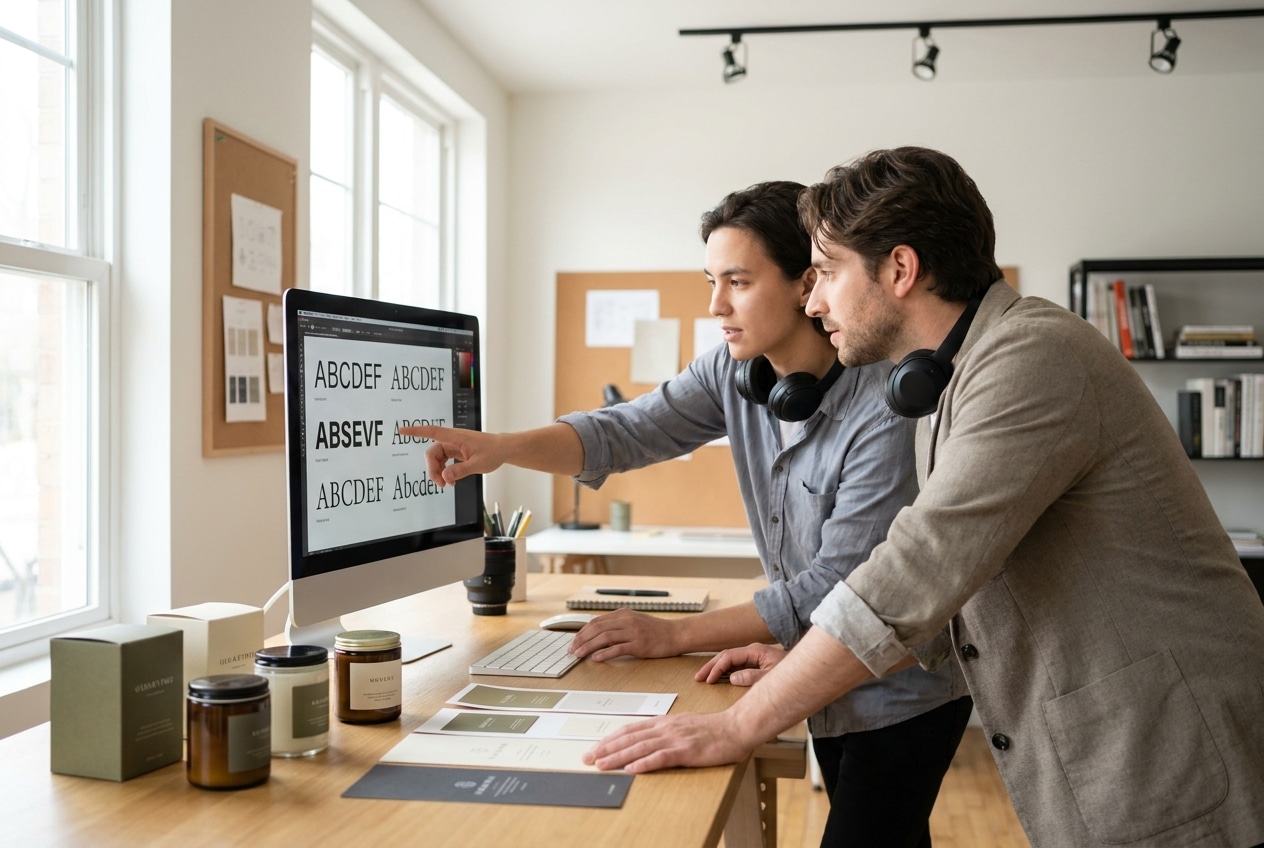
เทคนิคเลือกฟอนต์ออกแบบป้ายและฉลากสินค้า ให้แบรนด์ดูโปร
ฟอนต์หรือรูปแบบตัวอักษรไม่ใช่เป็นเพียงองค์ประกอบเพื่อความสวยงาม แต่คือ “เสียง” ของแบรนด์ที่สื่อสารกับลูกค้าโดยตรง การเลือกฟอนต์ที่เหมาะสมสามารถยกระดับสินค้าธรรมดาให้ดูพรีเมียม สร้างความน่าเชื่อถือ และทำให้แบรนด์เป็นที่จดจำได้ในทันที ในทางกลับกัน การเลือกฟอนต์ที่ผิดพลาดอาจทำให้สินค้าดูด้อยค่าและไม่น่าสนใจ
หัวใจสำคัญของการเลือกฟอนต์ที่มืออาชีพใช้
ก่อนจะลงลึกในรายละเอียด มีหลักการสำคัญที่ควรทำความเข้าใจ เพื่อเป็นแนวทางในการตัดสินใจเลือกฟอนต์สำหรับงานออกแบบโลโก้ ป้ายโฆษณา และฉลากสินค้าให้มีประสิทธิภาพสูงสุด
- ความอ่านง่าย (Readability) คือหัวใจสำคัญที่สุดของการออกแบบป้ายและฉลากสินค้า ข้อมูลต้องถูกสื่อสารอย่างรวดเร็วและชัดเจนบนชั้นวางสินค้า
- ความสอดคล้องกับแบรนด์ (Brand Consistency) ฟอนต์ต้องสะท้อนบุคลิกของแบรนด์ ไม่ว่าจะเป็นความหรูหรา, ความทันสมัย, ความเป็นธรรมชาติ หรือความสนุกสนาน
- ความเรียบง่าย (Simplicity) การใช้ฟอนต์จำนวนน้อย (ไม่เกิน 2-3 แบบ) และสร้างลำดับชั้นของข้อมูลที่ชัดเจน คือกุญแจสู่การออกแบบที่ดูเป็นมืออาชีพและไม่รกสายตา
การเรียนรู้ เทคนิคเลือกฟอนต์ออกแบบป้ายและฉลากสินค้า ให้แบรนด์ดูโปร เป็นทักษะที่จำเป็นสำหรับผู้ประกอบการ SME และนักออกแบบที่ไม่ควรมองข้าม เพราะฟอนต์มีอิทธิพลโดยตรงต่อการรับรู้ของผู้บริโภค มันสามารถสร้างความประทับใจแรกพบ บอกเล่าเรื่องราวของแบรนด์ และสื่อสารข้อมูลสำคัญของผลิตภัณฑ์ได้อย่างมีประสิทธิภาพ การเลือกฟอนต์ที่ถูกต้องไม่เพียงแต่ช่วยให้ฉลากสินค้าดูสวยงาม แต่ยังเป็นเครื่องมือทางการตลาดที่ทรงพลังในการสร้างแบรนด์ให้โดดเด่นและน่าจดจำในตลาดที่มีการแข่งขันสูง
ในโลกธุรกิจปัจจุบันที่ลูกค้าตัดสินใจซื้อสินค้าในเวลาเพียงไม่กี่วินาที ป้ายและฉลากสินค้าจึงเปรียบเสมือนพนักงานขายที่เงียบที่สุด การออกแบบองค์ประกอบทุกส่วนอย่างพิถีพิถัน โดยเฉพาะการเลือกใช้ตัวอักษร จะช่วยดึงดูดสายตา สื่อสารคุณค่า และสร้างความไว้วางใจได้ทันที ความรู้นี้จึงเป็นสิ่งจำเป็นสำหรับเจ้าของธุรกิจที่ต้องการสร้างแบรนด์ให้แข็งแกร่ง นักการตลาดที่ดูแลภาพลักษณ์สินค้า และกราฟิกดีไซเนอร์ที่รับหน้าที่ออกแบบบรรจุภัณฑ์ โดยกระบวนการเลือกฟอนต์ควรเกิดขึ้นตั้งแต่ขั้นตอนการสร้างอัตลักษณ์ของแบรนด์ (Brand Identity) เพื่อให้การสื่อสารทั้งหมดเป็นไปในทิศทางเดียวกัน
หลักการพื้นฐานที่ต้องยึดมั่นในการเลือกฟอนต์
การเลือกฟอนต์ที่ดีไม่ได้ขึ้นอยู่กับความชอบส่วนตัว แต่ตั้งอยู่บนหลักการออกแบบที่ผ่านการพิสูจน์แล้ว เพื่อให้แน่ใจว่าผลลัพธ์ที่ได้จะสามารถสื่อสารได้อย่างมีประสิทธิภาพและสร้างภาพลักษณ์ที่ดีให้กับแบรนด์
ความชัดเจนต้องมาก่อนความสวยงาม (Readability First)
ฉลากสินค้าและป้ายโฆษณามีหน้าที่หลักในการให้ข้อมูล ไม่ว่าจะเป็นชื่อสินค้า, ส่วนประกอบ, หรือวันหมดอายุ ดังนั้น ฟอนต์ที่เลือกใช้ต้องอ่านง่ายเป็นอันดับแรกเสมอ ควรหลีกเลี่ยงฟอนต์ที่มีความซับซ้อน ตกแต่งมากเกินไป หรือมีเส้นที่บางหรือหนาจนเกินพอดี โดยเฉพาะเมื่อต้องย่อขนาดลงบนฉลากจริง ฟอนต์ที่ดูสวยงามบนหน้าจอคอมพิวเตอร์อาจอ่านไม่ออกเมื่อถูกพิมพ์ลงบนบรรจุภัณฑ์ขนาดเล็ก ดังนั้นควรทดสอบการมองเห็นในขนาดใช้งานจริงเสมอ
เลือกฟอนต์ให้ตรงกับบุคลิกของแบรนด์ (Brand Personality)
ฟอนต์แต่ละรูปแบบให้อารมณ์และความรู้สึกที่แตกต่างกัน การเลือกฟอนต์ที่สอดคล้องกับบุคลิกของแบรนด์จะช่วยเสริมสร้างภาพลักษณ์ให้แข็งแกร่งขึ้น
- ฟอนต์มีเชิง (Serif): ฟอนต์ที่มีขีดเล็กๆ ที่ปลายตัวอักษร มักให้ความรู้สึกคลาสสิก, เป็นทางการ, หรูหรา, และน่าเชื่อถือ เหมาะสำหรับแบรนด์ที่ต้องการสร้างภาพลักษณ์ที่ดูภูมิฐานและมีประวัติศาสตร์ยาวนาน เช่น สินค้ากลุ่มพรีเมียม, บริการด้านการเงิน หรือแบรนด์ที่เน้นคุณภาพแบบดั้งเดิม
- ฟอนต์ไม่มีเชิง (Sans-serif): ฟอนต์ที่ไม่มีขีดที่ปลายตัวอักษร มีลักษณะเรียบง่าย สะอาดตา ให้ความรู้สึกทันสมัย, เป็นมิตร, และเข้าถึงง่าย เหมาะสำหรับแบรนด์เทคโนโลยี, สินค้าสำหรับคนรุ่นใหม่, ผลิตภัณฑ์เพื่อสุขภาพ หรือแบรนด์ที่ต้องการสื่อสารความเรียบง่ายและตรงไปตรงมา
การเลือกฟอนต์ผิดอารมณ์สามารถเปลี่ยนการรับรู้ของผลิตภัณฑ์ทั้งชิ้นได้ทันที ลองนึกภาพผลิตภัณฑ์ออร์แกนิกที่ใช้ฟอนต์แบบดิจิทัลล้ำยุค หรือแอปพลิเคชันใหม่ล่าสุดที่ใช้ฟอนต์แบบคลาสสิก ความรู้สึกขัดแย้งนี้อาจทำให้ผู้บริโภคเกิดความสับสนและไม่ไว้วางใจในตัวแบรนด์
เทคนิคการจับคู่และจัดวางฟอนต์อย่างมืออาชีพ
เมื่อเข้าใจหลักการพื้นฐานแล้ว ขั้นต่อไปคือการนำฟอนต์มาใช้งานจริงอย่างมีกลยุทธ์ เพื่อสร้างสรรค์งานออกแบบที่ลงตัวและมีประสิทธิภาพ
กฎทองคำ: ใช้ฟอนต์ไม่เกิน 2–3 รูปแบบ
การใช้ฟอนต์หลากหลายชนิดในงานออกแบบชิ้นเดียวจะทำให้ดูรก สับสน และไม่เป็นมืออาชีพ แนวทางที่ดีที่สุดคือการเลือกใช้ฟอนต์ไม่เกิน 2-3 รูปแบบ และกำหนดหน้าที่ของแต่ละฟอนต์ให้ชัดเจน เช่น:
- ฟอนต์หลัก (Primary Font): ใช้สำหรับหัวข้อที่สำคัญที่สุด เช่น ชื่อสินค้า หรือชื่อแบรนด์ ควรเป็นฟอนต์ที่โดดเด่นและสะท้อนบุคลิกแบรนด์ได้ดีที่สุด
- ฟอนต์รอง (Secondary Font): ใช้สำหรับหัวข้อย่อย หรือข้อความที่ต้องการเน้นรองลงมา ควรเป็นฟอนต์ที่อ่านง่ายและเข้ากันได้ดีกับฟอนต์หลัก
- ฟอนต์เนื้อหา (Body Font): ใช้สำหรับข้อความรายละเอียดต่างๆ เช่น ส่วนประกอบ หรือวิธีใช้ ควรเน้นฟอนต์ที่อ่านง่ายที่สุดแม้จะมีขนาดเล็ก